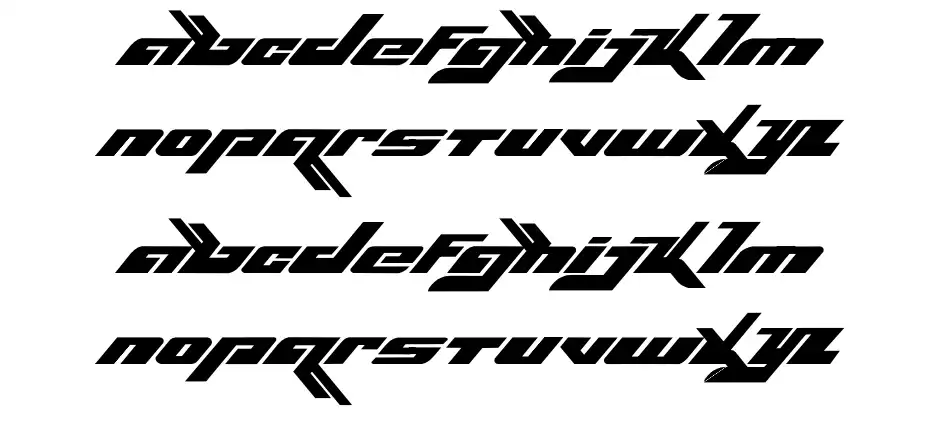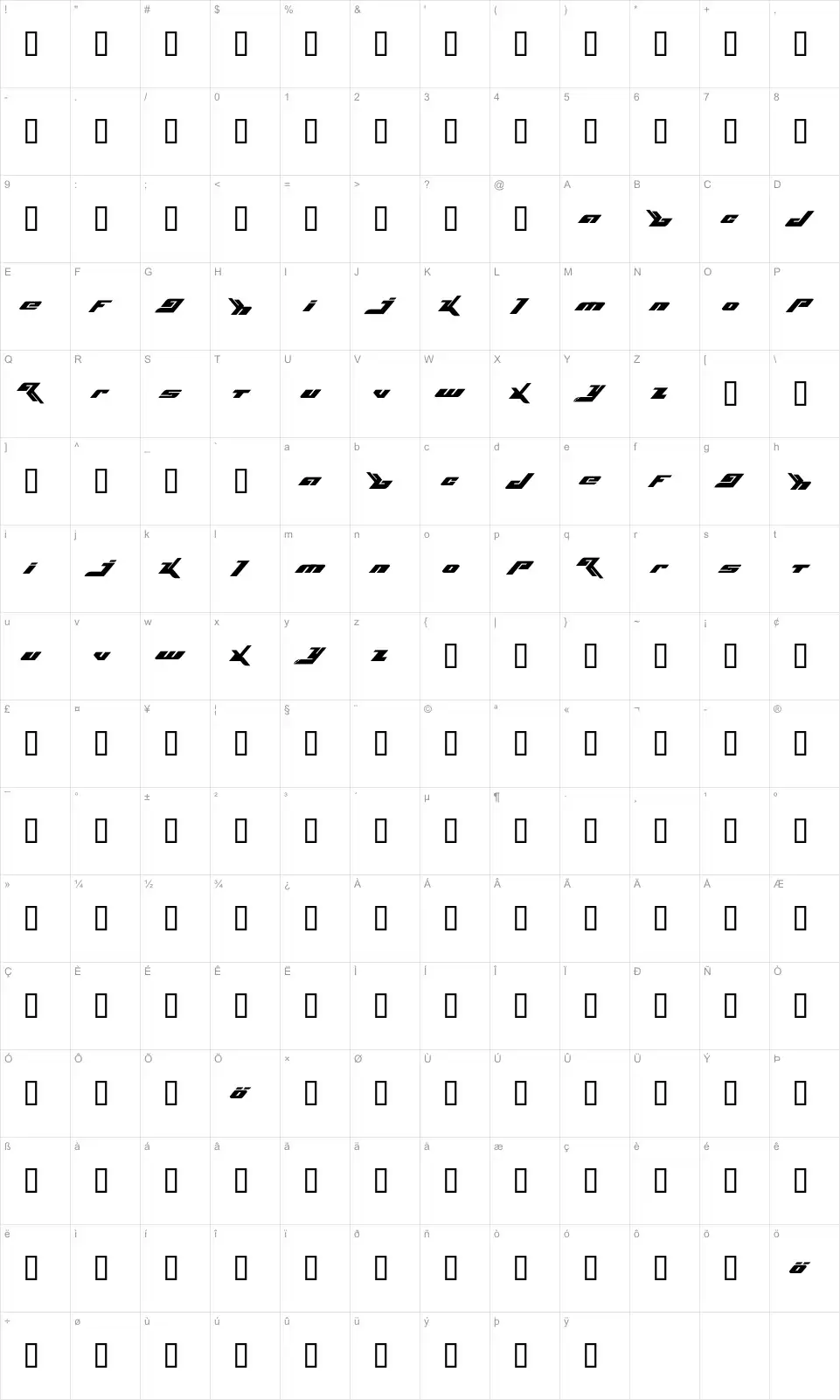
Bjork Font – Download Grátis
A fonte Bjork Font, criada pelo designer Animus, é uma seleção ideal para aqueles buscando um efeito techno moderno. Frequentemente utilizada em designs digitais e de interação online, ela oferece um estilo clean e futurista que se adequa perfeitamente à categoria techno. Esta font está licenciada sob o termo gratuito, facilitando a sua adesão por qualquer designer ou desenvolvedor de software. A font é disponível em formato TTF, permitindo a sua utilização em diversos ambientes digitais. Adicionada recentemente em 12 de julho de 2022, já tem 2098 downloads, demonstrando seu valor e popularidade. Com um tamanho de 11 KB, é uma opção leve e eficiente para projetos que exigem uma boa velocidade de carregamento. Experimente o Bjork Font para adicionar um toque moderno e tecnológico a qualquer projeto.